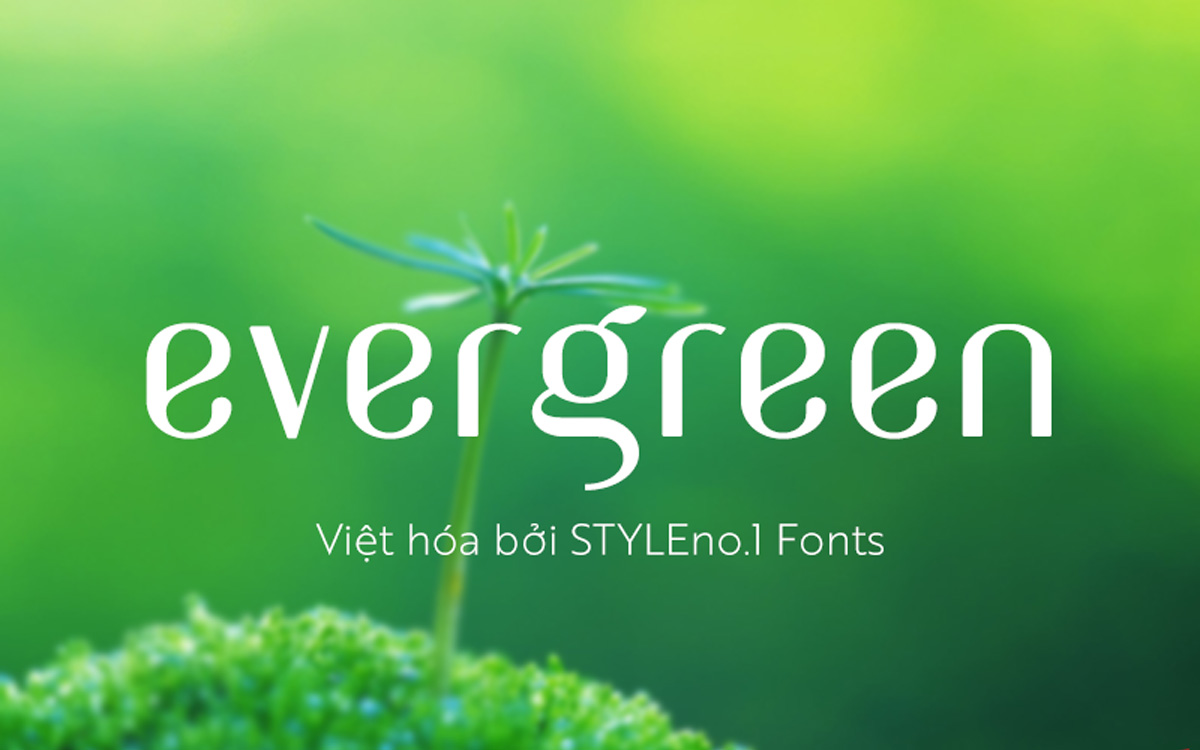
Font chữ mỏng hiện đại, sang trọng, thanh lịch cho thời trang, tạp trí SVN-Evergreen
Trong thế giới thiết kế đồ họa cao cấp, lựa chọn một kiểu chữ phù hợp chính là chìa khóa vàng để nâng tầm giá trị thương hiệu và truyền tải cảm xúc sản phẩm một cách trọn vẹn nhất. Bộ font SVN-Evergreen ra đời như một biểu tượng của vẻ đẹp tinh tế, sở hữu những đường nét mảnh mai, thanh thoát nhưng vô cùng hiện đại và cuốn hút. Đây chính là giải pháp typography hoàn hảo được các nhà thiết kế săn đón hàng đầu dành riêng cho các dự án thời trang, trang trí bìa tạp chí, nhận diện thương hiệu xa xỉ và các ấn phẩm truyền thông sang trọng.
Font Chữ Mỏng Hiện Đại, Sang Trọng, Thanh Lịch Cho Thời Trang, Tạp Chí SVN-Evergreen – Đỉnh Cao Của Typography Sáng Tạo
Khi nhắc đến thiết kế dành cho các ngành hàng xa xỉ như thời trang haute couture, mỹ phẩm cao cấp, trang sức hay các trang tạp chí nghệ thuật, tính thẩm mỹ của typography luôn đóng vai trò quyết định đến diện mạo thị giác của sản phẩm. SVN-Evergreen không chỉ đơn thuần là một phông chữ, mà còn là một tác phẩm nghệ thuật chữ được chế tác tỉ mỉ, kết hợp hoàn hảo giữa nét cổ điển quý phái và tinh thần hiện đại tối giản. Với cấu trúc nét mỏng chuẩn mực, khoảng cách ký tự được phân bổ tối ưu, font chữ mỏng hiện đại sang trọng thanh lịch này mang lại một tinh thần hoàn toàn mới, giúp mọi thông điệp truyền thông trở nên đẳng cấp, thu hút ánh nhìn ngay từ cái nhìn đầu tiên.
1. Thiết Kế Nét Chữ Thin Elegant Chuẩn Phong Cách Thời Trang Cao Cấp
Điểm đặc trưng lớn nhất của SVN-Evergreen nằm ở những đường nét mỏng mảnh (Ultra Thin/Light) được gọt giũa vô cùng sắc sảo. Cấu trúc chữ được thiết kế dựa trên tỷ lệ hình học chuẩn xác, cân bằng tuyệt đối giữa chiều cao và chiều rộng của từng ký tự. Nét mảnh của SVN-Evergreen không hề tạo cảm giác yếu ớt, mà ngược lại, nó thể hiện sự kiêu hãnh, thanh lịch và cực kỳ hiện đại. Đây là phong cách thiết kế đặc trưng thường thấy ở các thương hiệu thời trang thế giới như Vogue, Harper’s Bazaar, Chanel hay Dior. Khi được ứng dụng làm tiêu đề hoặc logo, SVN-Evergreen tạo nên một khoảng không gian thở đầy tính nghệ thuật, giúp thiết kế của bạn thoát khỏi sự thô cứng của các dòng font chữ truyền thống.
2. Khả Năng Ứng Dụng Đa Dạng Trong Thiết Kế Tạp Chí Và Layout Editorial
Đối với các nhà thiết kế dàn trang tạp chí (editorial design), việc tìm kiếm một bộ font vừa đảm bảo tính thẩm mỹ cao vừa giữ được sự hài hòa trên tổng thể trang sách là điều không hề dễ dàng. SVN-Evergreen giải quyết triệt để bài toán này nhờ vào tính linh hoạt tuyệt vời trong cách sắp xếp. Font chữ này phát huy tối đa sức mạnh khi xuất hiện trên các trang bìa tạp chí thời trang, tiêu đề bài viết nghệ thuật, các câu quote truyền cảm hứng hay thông điệp chính của bộ sưu tập. Sự tương phản giữa các nét chữ mỏng và khoảng trắng trên trang giấy tạo nên một nhịp điệu thị giác êm ái, hướng người đọc tập trung vào nội dung mà không gây cảm giác nhạt nhòa.
3. Hỗ Trợ Tiếng Việt Tối Ưu Với Hệ Thống Ký Tự Việt Hóa Chuẩn Xác
Một thách thức lớn đối với các nhà thiết kế Việt Nam khi sử dụng các font chữ nước ngoài là dấu tiếng Việt thường bị thô, làm mất đi dáng vẻ ban đầu của bộ phông. Với phiên bản SVN-Evergreen, toàn bộ hệ thống dấu tiếng Việt đã được trau chuốt tỉ mỉ bởi các chuyên gia việt hóa hàng đầu. Các dấu thanh (sắc, huyền, hỏi, ngã, nặng) cũng như các dấu phụ (nón, râu) được tinh chỉnh về mặt tỷ lệ, khoảng cách và góc nghiêng sao cho hòa hợp hoàn toàn với nét chữ mỏng thanh thoát. Nhờ đó, bạn hoàn toàn có thể tự tin sáng tạo các dự án thiết kế tiếng Việt mà vẫn giữ nguyên được thần thái sang trọng, cao cấp vốn có của bản gốc.
4. Tích Hợp Bộ Ký Tự Thay Thế (Ligatures & Stylistic Alternates) Phong Phú
Để tăng thêm tính độc bản cho các sản phẩm thiết kế, SVN-Evergreen cung cấp một hệ thống ký tự thay thế (Alternate Characters) và ký tự nối (Ligatures) cực kỳ phong phú. Các điểm dính chữ, đường nét uốn lượn tinh tế ở các chữ cái đặc biệt giúp nhà thiết kế dễ dàng biến tấu, tạo ra những mẫu logo, biểu trưng hay tiêu đề độc nhất vô nhị mà không cần tốn quá nhiều thời gian vẽ lại vector thủ công. Tính năng OpenType nâng cao này cho phép bạn tự do bay bổng với ý tưởng sáng tạo, đem đến cái nhìn đa chiều và giàu tính cảm xúc hơn cho từng tác phẩm typography.
5. Tối Ưu Hoàn Hảo Cho Cả In Ấn Ấn Phẩm Và Kỹ Thuật Số (Digital Display)
SVN-Evergreen được số hóa với độ phân giải vector cực kỳ chính xác, giúp hiển thị sắc nét trên mọi chất liệu và nền tảng. Dù bạn sử dụng font chữ này để in ấn trên các chất liệu cao cấp như giấy mỹ thuật, ép kim (hot foil stamping), dập nổi bao bì sản phẩm hay hiển thị trên màn hình kỹ thuật số độ phân giải cao (Retina, 4K) cho website, banner quảng cáo, ứng dụng di động và mạng xã hội, SVN-Evergreen vẫn giữ nguyên độ mịn màng, không bị vỡ nét hay mờ nhòe. Điều này đảm bảo tính thống nhất trọn vẹn cho toàn bộ hệ thống nhận diện thương hiệu từ online đến offline.
Nhờ những ưu điểm vượt trội về mặt thẩm mỹ và công năng, font chữ mỏng hiện đại SVN-Evergreen trở thành sự lựa chọn hàng đầu trong nhiều lĩnh vực sáng tạo khác nhau:
• Thiết kế nhận diện thương hiệu thời trang & mỹ phẩm: Tạo dựng logo, nhãn mác, bao bì son, nước hoa, túi xách cao cấp.
• Tạp chí & Ấn phẩm nghệ thuật: Dàn trang bìa, thiết kế tiêu đề chuyên mục, catalogue sản phẩm, lookbook thời trang theo mùa.
• Truyền thông & Marketing kỹ thuật số: Tạo banner quảng cáo Facebook, Instagram Stories, poster sự kiện âm nhạc, triển lãm nghệ thuật.
• Thiết kế thiệp cưới & Sự kiện cao cấp: Thiệp mời đám cưới sang trọng, menu nhà hàng 5 sao, bảng tên khách mời mang phong cách tối giản (Minimalism).
• Nghệ thuật chữ (Typography Art): Tạo các câu quote nghệ thuật, trang trí không gian nội thất, bìa sách và đĩa nhạc.Để đạt hiệu quả thị giác tối đa khi sử dụng SVN-Evergreen, các chuyên gia thiết kế khuyến nghị một số mẹo phối chữ (Font Pairing) đơn giản nhưng cực kỳ hiệu quả: